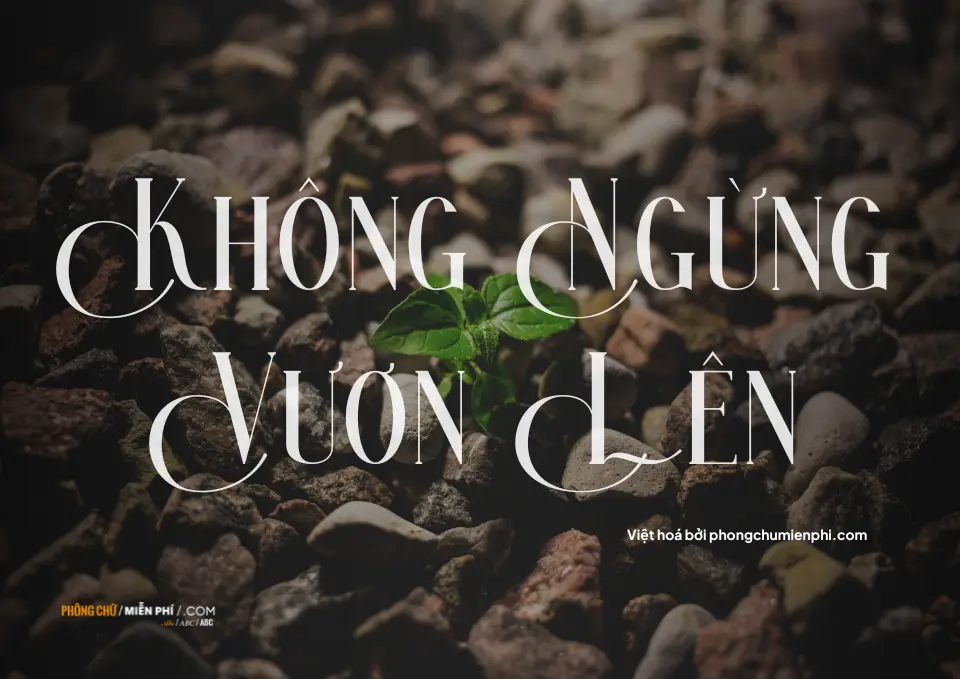
Tên font: Font Việt hoá Activists Regular
Phông chữ PCMP Activists Regular là một kiểu chữ Serif hiện đại mới. Bộ sưu tập Serif này hoàn hảo cho các dự án xây dựng thương hiệu trong mọi loại hình doanh nghiệp và là một lựa chọn thanh lịch, mang đến phong cách thiết kế đơn giản, hiện đại, tối giản, tinh tế, phù hợp cho logo hoặc danh thiếp công ty, thiệp quà tặng, in bìa áo thun, ảnh chụp poster thu nhỏ và trích dẫn, v.v. Đây là một sự bổ sung tuyệt vời cho thiết kế đồ họa cho mọi loại dự án đồ họa như logo hoặc danh thiếp công ty, poster, ảnh chụp trích dẫn, v.v.